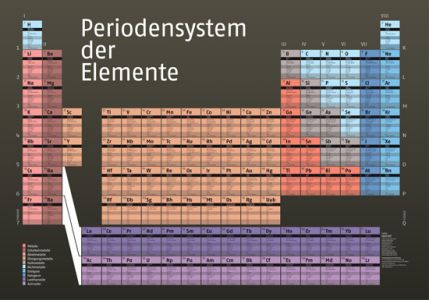
Periodensystem in lesefreundlich
Ich bin sehr stolz, endlich das fertige Periodensystem der Elemente präsentieren zu können. Komplett in FF Fago gesetzt und auf 100 x 69 cm gedruckt.
Yeah Vorschusslorbeeren, ich als ehemaliger Chemie und Biologie-Leistungskursler bin natürlich an "neuen" Darstellungen des Periodensystems interessiert.
Man müsste halt das Ding "richtig" sehen können. Vielleicht ein bisschen zu "künstlerisch" von der Anlage her. "Periodensystem der Elemente" ist mir aber definitiv zu gross gesetzt.
DAS ist eigentlich das Einsatzgebiet der Fago!
Dieses Nato-Grün (?) als Fondfarbe finde ich – ehrlich gesagt – nicht so gut. Erleichtert sowas die Lesbarkeit? Oder war die alte Schultafel die Inspiration?
Und sowas gibt es auch schon, ähnlich gut, dazu noch viersprachig ... Okay, nicht in der schönen Fago sondern in der „umstrittenen” Rotis (Hausschrift der Firma Merck) gesetzt.
Jaja, daran war ich mal beteiligt, ... deshalb meine (selbst)kritischen Anmerkungen ... ;)
puh, die Schrift drängt sich in eurer Anwendung unangenehm, ohne understatement, in den Vordergrund.
Ich lebe in Stuttgart und dort ist das Leitsystem der VVS (ein Verkehrsverbund; U-Bahnen, S-Bahnen, Busse) auch mit der Rotis "bespielt". Ähnlicher Effekt …
OK Realität – für (manches) Geld würde ich die Rotis auch einsetzen, wenn ich es nicht vorab verhindern könnte.
Dieses Nato-Grün (?) als Fondfarbe finde ich – ehrlich gesagt – nicht so gut.
Das finde ich nun in keiner Weise störend, für mich paßt das farblich alles sehr gut.
Und sowas gibt es auch schon, ähnlich gut
Aber nicht doch. Euer Plakat wirkt im Vergleich ausgesprochen unruhig.
so war das nicht gemeint. Ich habe da was falsch verstanden. Ich hatte gedacht, Christian beansprucht für sich, daß erste Periodensystem für die Allgemeinheit gestaltet zu haben. Das ist natürlich Quatsch.
Ich habe mich nur mit dem Periodensystem von Merck ziemlich lange herumgequält. Die haben ein sehr striktes CD und es bleiben einem kaum gestalterische Möglichkeiten (schon gar nicht was die Typo betrifft).
Christians Poster ist natürlich klasse! … Bis auf die Hintergrundfarbe ... die finde ich immer noch komisch ... :cry:
Das Plakat sieht in der Vorschau gut aus. Aber ich frage mich ob die Schrift gut zu lesen sein wird, da die Hintergrundfarben sehr dunkel sind.
>Die haben ein sehr striktes CD und es bleiben einem kaum gestalterische Möglichkeiten (schon gar nicht was die Typo betrifft).
Sorry, ich wollte nicht an eurer Arbeit herumnörgeln, nur zum Ausdruck bringen das die "Deko" Rotis für solche Aufgaben fehl am Platz ist. So wie als Leitsystemschrift für einen Verkehrsverbund …
das natogrün ist in wirklichkeit ein warmes anthrazit, es lebe die Komprimierung. :-)
Ich habe selber kaum Ahnung von chemischen Details, daher habe ich mir von Lars helfen lassen. Er hat die Kennzahlen ausgewählt und auch rausgesucht. Mit einer Freundin habe ich dann in endlosen Sitzungen Korrektur gelesen und ich kann dich bestätigen, Sharif, es ist nicht in fünf Minuten getan. :-) Ich finde bei der Fago die Tabellenziffern einfach klasse und wollte die schon immer für sowas nehmen. Die Schriftgröße von den Kennzahlen ist jetzt bei 19 Punkt, was man bequem im Sitzen lesen kann.
Bei der Gestaltung dachte ich an den Chemiestudenten, der ein Zimmer mit vier Wänden zur Verfügung hat. Eine Wand hat die Tür und den Kleiderschrank, eine Wand das Fenster. Eine Wand ist mit Spiegel und Fotos voll und über dem Schreibtisch wäre noch Platz für ein Periodensystem. Damit das Periodensystem auf der weißen Wand einen guten Eindruck macht, habe ich das warme Anthrazit genommen. Was ich beim Titelschriftzug wieder gemerkt habe: die Fago ist einfach schlecht zugerichtet. Die Zurichtung habe ich komplett von Hand gemacht.
Die Uni Darmstadt hat gerade dieses System in extra groß bekommen für einen Hörsaal. Ich warte da noch auf Fotos, habs selber noch nicht hängen gesehen. Was mich besonders freut, ist dass der Uni-Mitarbeiter das System als sehr wissenschaftlich bezeichnet hat. Danach konnte ich eindeutig ruhiger schlafen.
Hier noch ein Bild vom ganzen System
Da melde ich mich als Chemiker doch mal zu Wort. Ein paar Fragen habe ich dann doch zu deinem Periodensystem.
1. Die Gestaltung ist ruhig und übersichtlich, aber trotzdem nicht langweilig.
2. Warum sind die Nebengruppen nicht nummeriert?
3. Warum wird nicht die neue IUPAC-Nomenklatur für die Gruppen verwendet?
7. Die Legende zu den einzelnen Elementen unten rechts finde ich etwas unüblich plaziert und unscheinbar. Ich denke aber, damit kommt man nach einer kurzen Eingewöhnung zu Recht. Als Chemiker ist man es halt gewohnt, dass meist ein einzelnes »Elementkästchen« nochmals herausgegriffen wird und in der Mitte über den Nebengruppen plaziert wird, wo dann die Legende angebracht wird.
Die Platzierung der Legende ist in der Tat eine Gestaltungsfrage gewesen. Ich finde die dort elegant untergebracht und hätte ein weiteres Kästchen als störend angesehen.